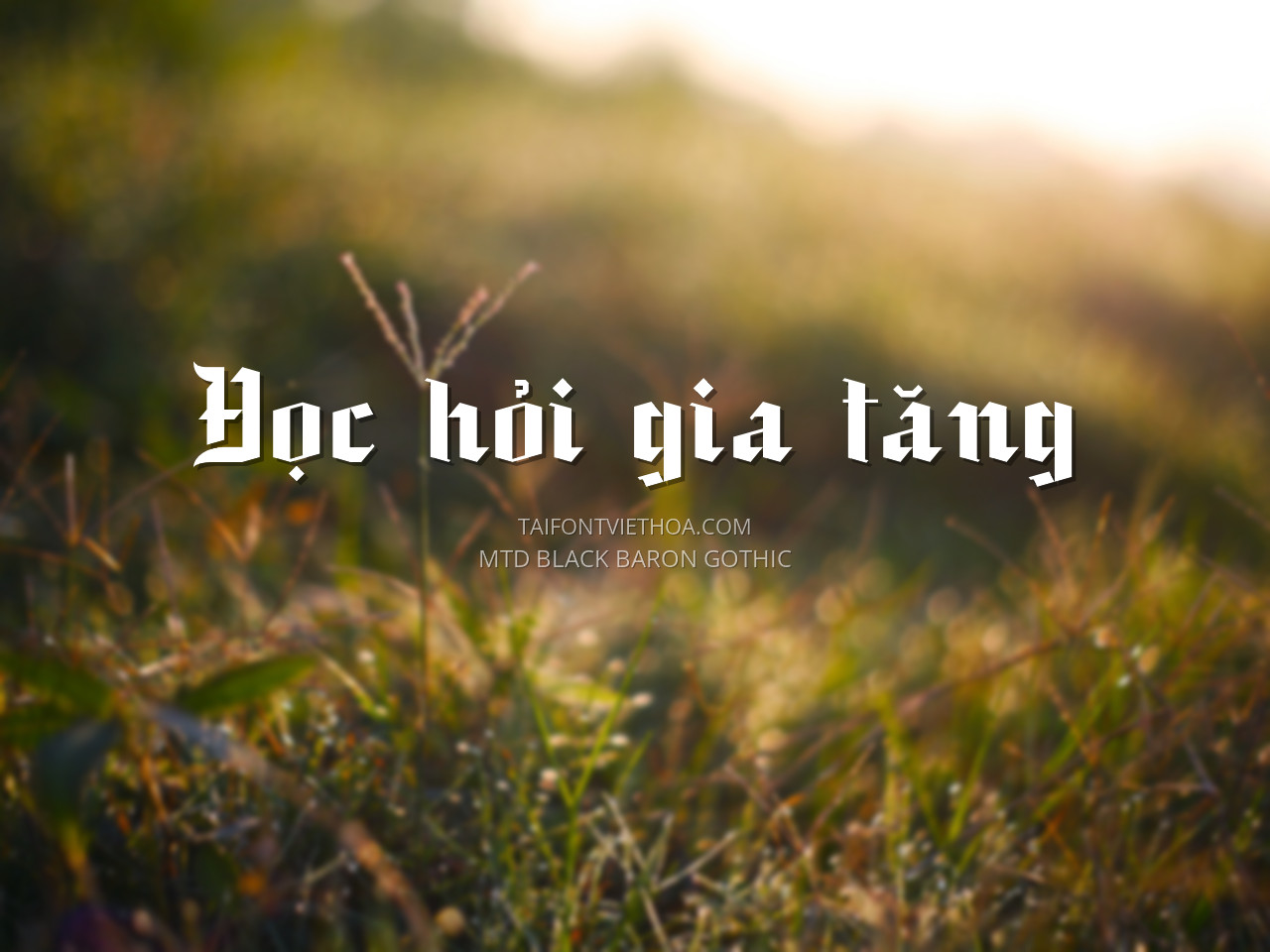
Font việt hóa MTD Black Baron Gothic
Giới thiệu về font Black Baron Gothic – Hơi thở cổ điển trong phong cách gothic quyền lực
Black Baron Gothic là một kiểu chữ display mang phong cách gothic cổ điển kết hợp hiện đại, được thiết kế với các đường nét mạnh mẽ, dứt khoát và đậm chất trình diễn. Font thường xuất hiện trong các thiết kế poster phim, bìa sách, tiêu đề game hoặc thương hiệu mang phong cách retro – gothic. Với kiểu dáng cao, góc cạnh, nhiều chi tiết thanh mảnh kết hợp các nét gãy mạnh, Black Baron Gothic tạo cảm giác uy nghi, quyền lực và đầy kịch tính. Font hỗ trợ bộ ký tự Latin mở rộng, tương thích với nhiều ngôn ngữ châu Âu hiện đại.
Phiên bản Việt hóa do Mộc Hạthực hiện đã bổ sung đầy đủ hệ thống dấu tiếng Việt, giữ nguyên kết cấu gothic đặc trưng của bản gốc, đồng thời đảm bảo tính ứng dụng cao trong các dự án thiết kế sử dụng tiếng Việt. Taifontviethoa.comđã chọn lọc và chia sẻ font Black Baron Gothic nhằm phục vụ cộng đồng thiết kế cần một kiểu chữ cổ điển nhưng đầy bản lĩnh, thích hợp với các dự án mang yếu tố lịch sử, huyền thoại hoặc fantasy.
Đặc điểm thiết kế đậm chất gothic và các ứng dụng lý tưởng
Font Black Baron Gothic có cấu trúc chữ cao, chân nhọn, phần thân chữ hẹp và các đường nét gãy khúc mạnh. Thiết kế của font phản ánh phong cách gothic truyền thống nhưng vẫn mang nét hiện đại đủ để ứng dụng vào các sản phẩm truyền thông số. Kiểu chữ này đặc biệt nổi bật khi sử dụng ở cỡ lớn, làm tiêu đề chính, logo hoặc biển hiệu ấn tượng.
Font phù hợp cho các dự án như: bìa truyện tranh, poster phim cổ trang – huyền bí, tiêu đề game hành động, banner lễ hội Halloween, logo thời trang gothic hoặc thương hiệu mang yếu tố giả tưởng. Ngành nghề phù hợp gồm: nghệ thuật, game, giải trí, thời trang độc lập, sách fantasy, âm nhạc rock, tổ chức sự kiện hoặc các thương hiệu mang tính bản sắc và huyền thoại.
Thiết kế: Alexander Bobrov
Thiết kế: Khurasan Studio